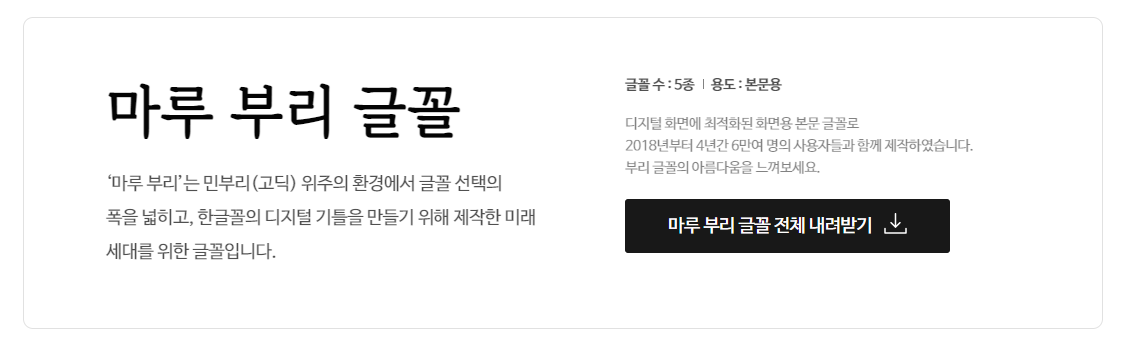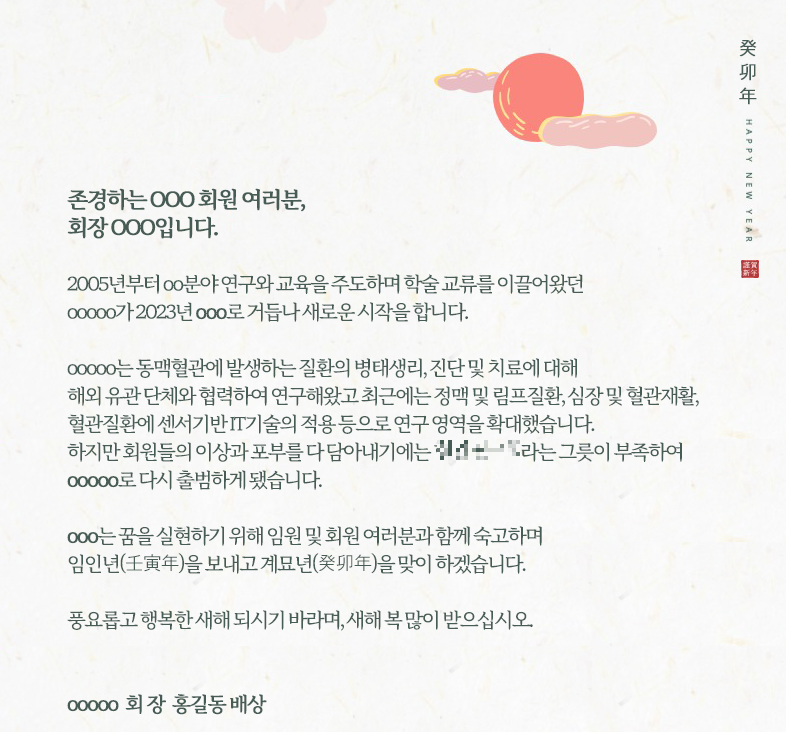
TTF 폰트 OTF 폰트 차이가 뭘까? 어떤 걸 사용하지?
얼마 전, 신년 인사 팝업을 디자인 하기 위해, 신년인사 분위기에 어울리는 폰트(Font)가 필요해졌습니다. 폰트는 유상으로 판매하는 유료폰트가 있고, 무상으로 배포하는 무료폰트가 존재합니다. 디자인으로 첨예한 이슈가 아니라면 대부분의 사용자라면 저작권 이슈로부터 자유로운 무료 폰트를 많이 사용하고자 할 것입니다.
그런 의미에서 <네이버 글꼴>은 기본적으로 많은 사람들이 사용하는 무료폰트를 배포하고 있습니다. 저도 이미 네이버 글꼴을 사용하고 있으나, 추가로 사용할만한 글꼴을 찾기 위해 네이버 폰트에 접속을 한 후, '마루 부리'라는 이름의 폰트를 사용하기로 했습니다.
TTF와 OTF 폰트의 차이점 살펴보기
간략하게 나마, 두 가지 폰트 타입의 차이점을 살펴보도록 합시다. 알고 사용하는 것과 모르고 그냥 쓰는 것에는 분명한 차이가 있을테니까요.
TTF - True Type Font
TTF는 1980년대에 애플이 Adobe의 대항마로 개발된 폰트저장 형식입니다. 보통 Microsoft 윈도우에 포함되면서 무료 라이선스가 되어 대중들에게 많이 알려졌습니다. 파워포인트, 엑셀, MS-Word 및 윈도우 기반의 포토샵 등에서도 오래도록 사용되어져 왔습니다. 윈도우 사용자에게는 바탕체, 굴림체, 궁서체 등이 유명하죠.
OTF - Open Type Font
OTF는 10여년 뒤 1990년대에 마이크로소프트가 개발한 후 어도비사와 함께 개발한 폰트저장 형식입니다. 리눅스, 매킨토시, 윈도우 등 다양한 OS환경에서 모니터 화면이던 인쇄물이던간에 동일한 모양을 출력해주기 위해 제작된 글꼴방식이죠. 주로 고해상도 출력이나 그래픽 작업에 많이 사용되고 있습니다.
TTF와 OTF의 차이점은?
두 폰트 타입의 가장 큰 차이점은 '베지어 곡선'을 구현하는 방식에 있습니다.
TTF는 2차원 베지어 방식(Quadratic Bezier)을 사용하고 있고, OTF는 3차원 베지어 방식(Cubic Bezier)으로 베지어 곡선을 사용하고 있습니다. 대충 생각해봐도 2차원 방식 보다는 3차원 방식의 곡선이 뭔가 더 세밀한 곡선을 그려줄 것 같죠? 맞습니다.
2차원 베지어 곡선은 1개의 조절점을 사용해서 생성됩니다.
그리고, 3차원 베지어 곡선은 2개의 조절점을 사용해서 곡선을 그려내게 됩니다.
일반적으로 베지어 곡선식의 차수가 높을수록 더 매끄러운 곡선으로 표현될 수 있다고 합니다. 이러한 관점에서 TTF 보다 OTF의 곡선구현이 상대적으로 정밀하고 깔끔하다고 볼 수 있습니다.
2차원 베지어 곡선이 그려지는 방식입니다. 딱 봐도 계산이 간단하겠죠? 연산이 간단하고 빠르기 때문에 주로 문서를 위한 폰트와 같은 곳에 사용됩니다. 곡선이 항상 그림 그리는 곳에서만 사용되는 것은 아닐 테니까요.
3차원 베지어 곡선이 그려지는 방식입니다. 차원 연산이 한번 더 들어가기 때문에, TTF보다는 상대적으로 느릴 수는 있지만, 고해상도 이미지 등에서는 보다 복잡한 곡선도 미려하게 그려낼 수 있게 됩니다. 그래서 그래픽이나 고해상도 출력물에 주로 사용됩니다.
그래서 결론은? TTF를 써? OTF를 써?
사실 일반 사용자라면 아무거나 사용해도 됩니다. 문서 작업을 주로 하는 분이라면 TTF를 써도 무방합니다. 그래픽 작업을 한다고 해도 모니터상에서 사용되는 그래픽 정도는 TTF를 사용해도 괜찮습니다. 다만 디자인 작업 결과물로 고해상도의 인쇄 출력물까지 만들어야 하는 경우라면 OTF를 사용하는 것이 선호됩니다.
한편 OTF를 사용하더라도, 모니터 해상도가 좋지 않다면 모니터에서의 구분은 크게 차이가 나지 않을 수도 있습니다. 글꼴의 미세한 곡선차이를 모니터 또한 잘 표현해주어야 하기 때문입니다.
그리고 TTF와 OTF의 구현속도 차이도 현재에는 크게 의미가 없습니다. PC 하드웨어가 엄청나게 발전해 있기 때문이죠.
그래서 한줄로 결론을 내 본다면, 2022년 마지막 날인 오늘 내일부터 2023년이 새로 시작되는 시점에서의 폰트 선택은 OTF입니다.^^ 그냥 더 좋다는 녀석을 사용하시면 됩니다.
마치며
그냥 TTF와 OTF의 만들어진 시기, 베지어 곡선을 그려내는 차이, 고해상도 그래픽에서의 장점 등을 이해하는 상태로 사용자의 취향에 따라 선택해서 설치/사용하면 되는 이슈입니다. 그래서 전 OTF.